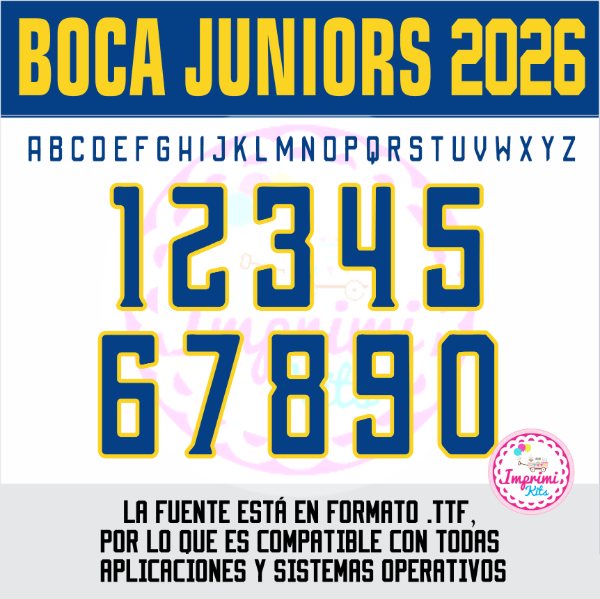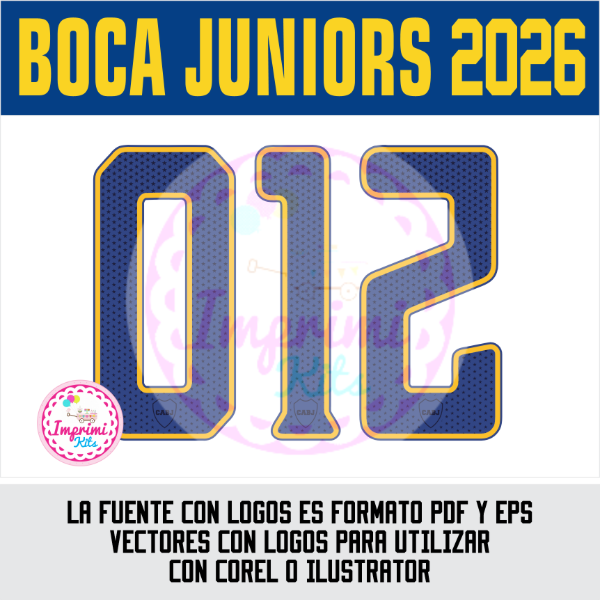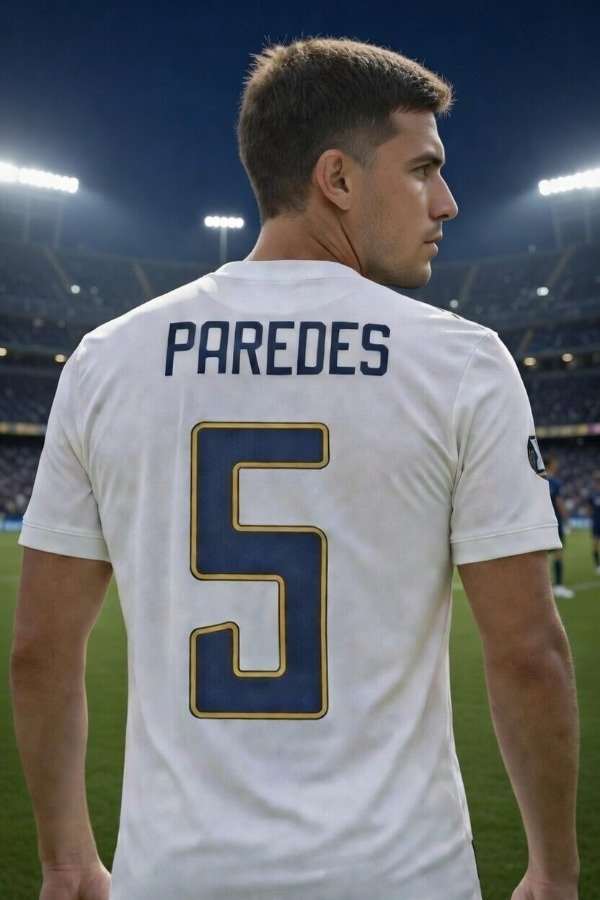
Tipografia Tipografía Boca Juniors 2026 Suplente Camiseta Ttf Numeros Dorsal DTF
Tipografía Números Fuente
Los vectores de numeros dorsales incluyen detalles y el logo oficial en el numero (VER FOTO 2)
Realizá todo tipo de creaciones con la tipografía utilizada actualmente en el club